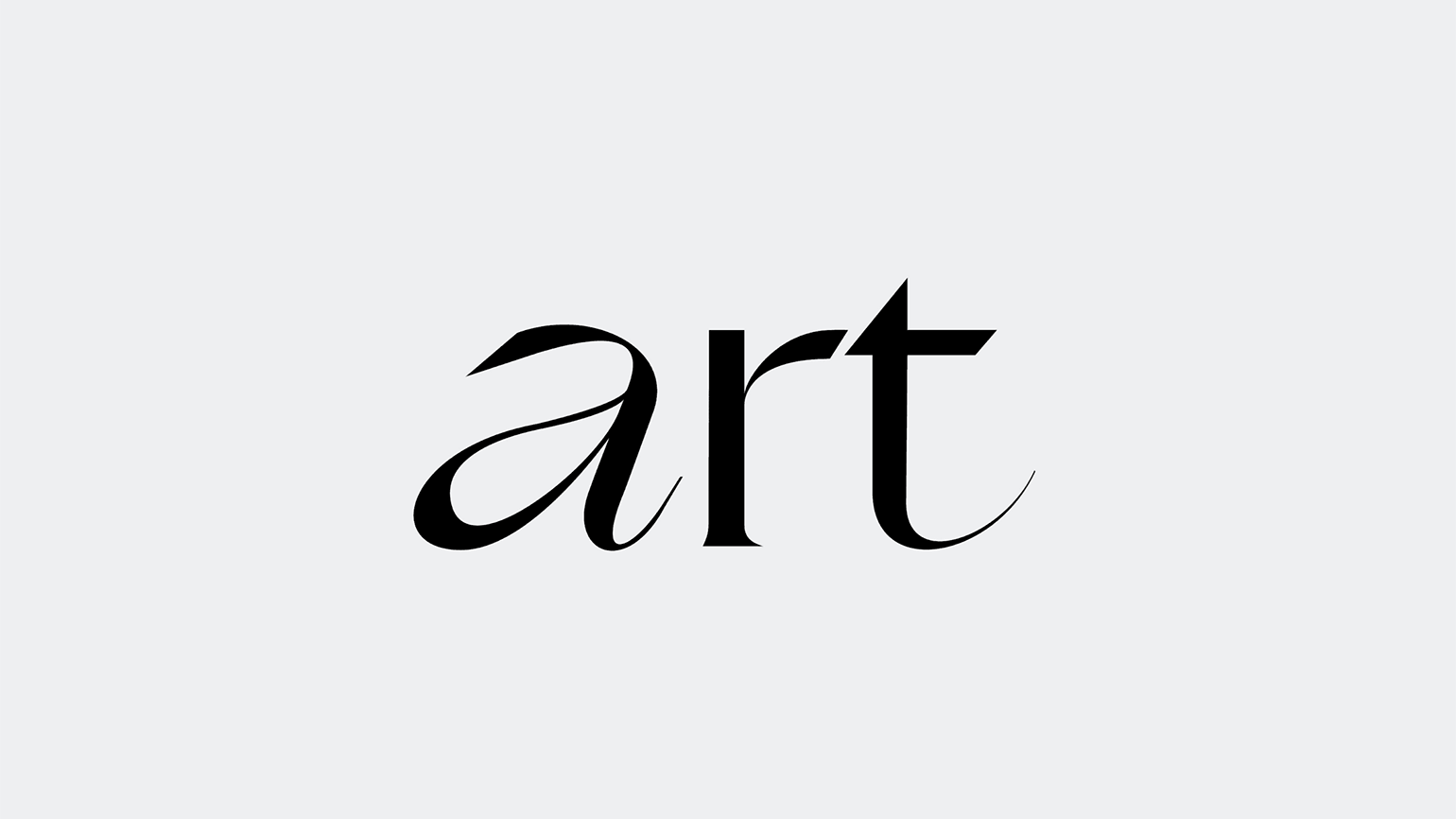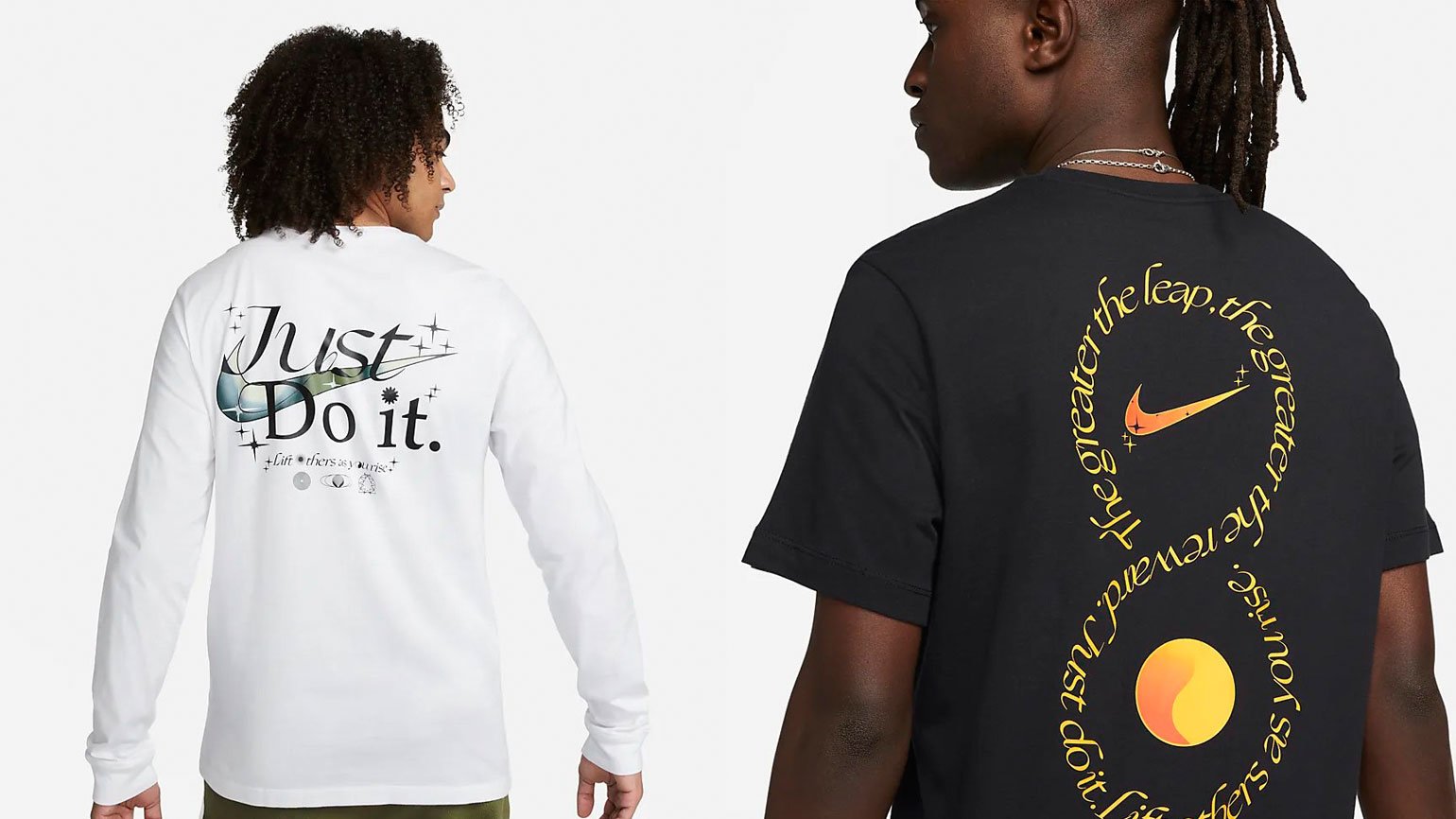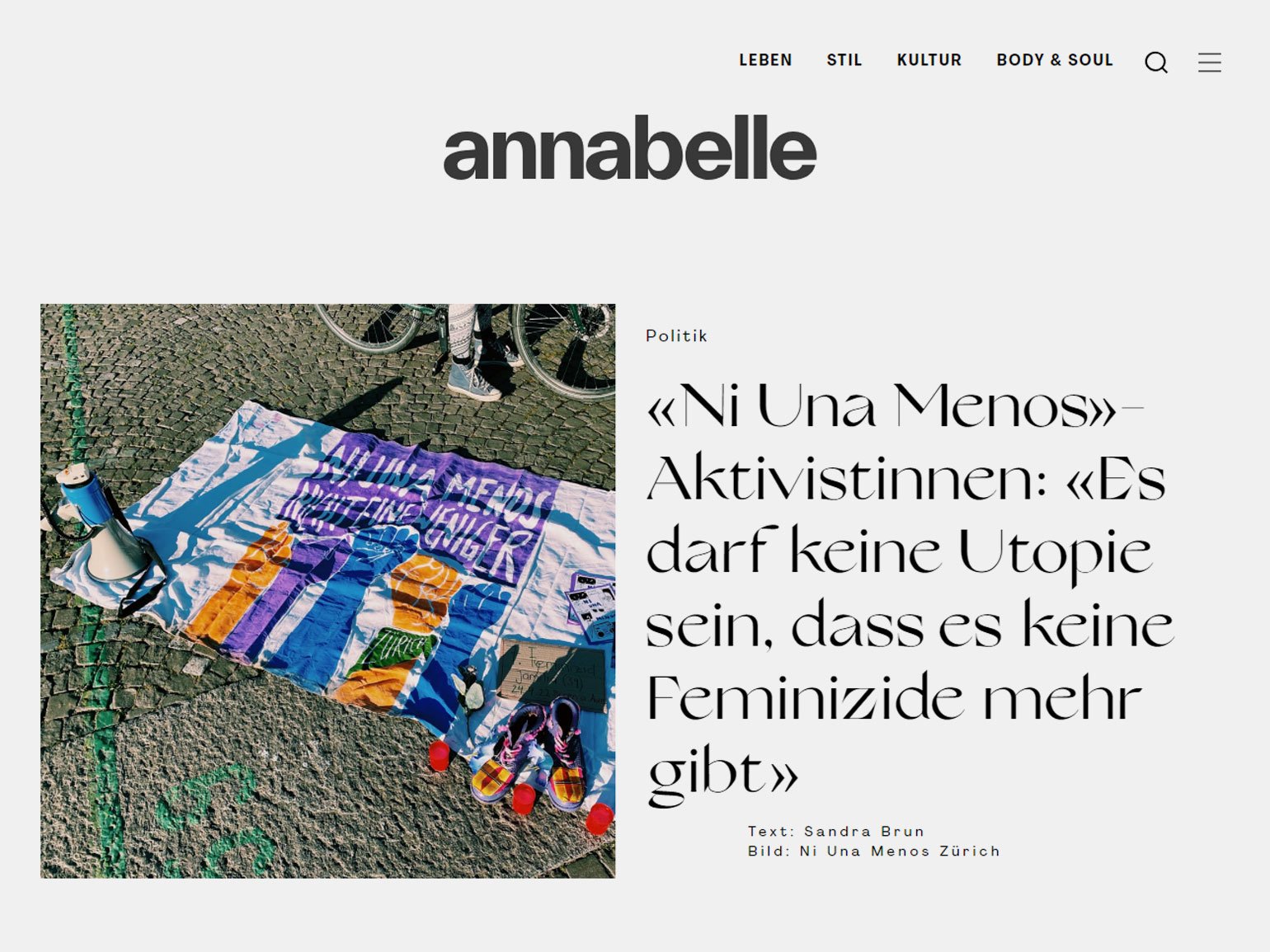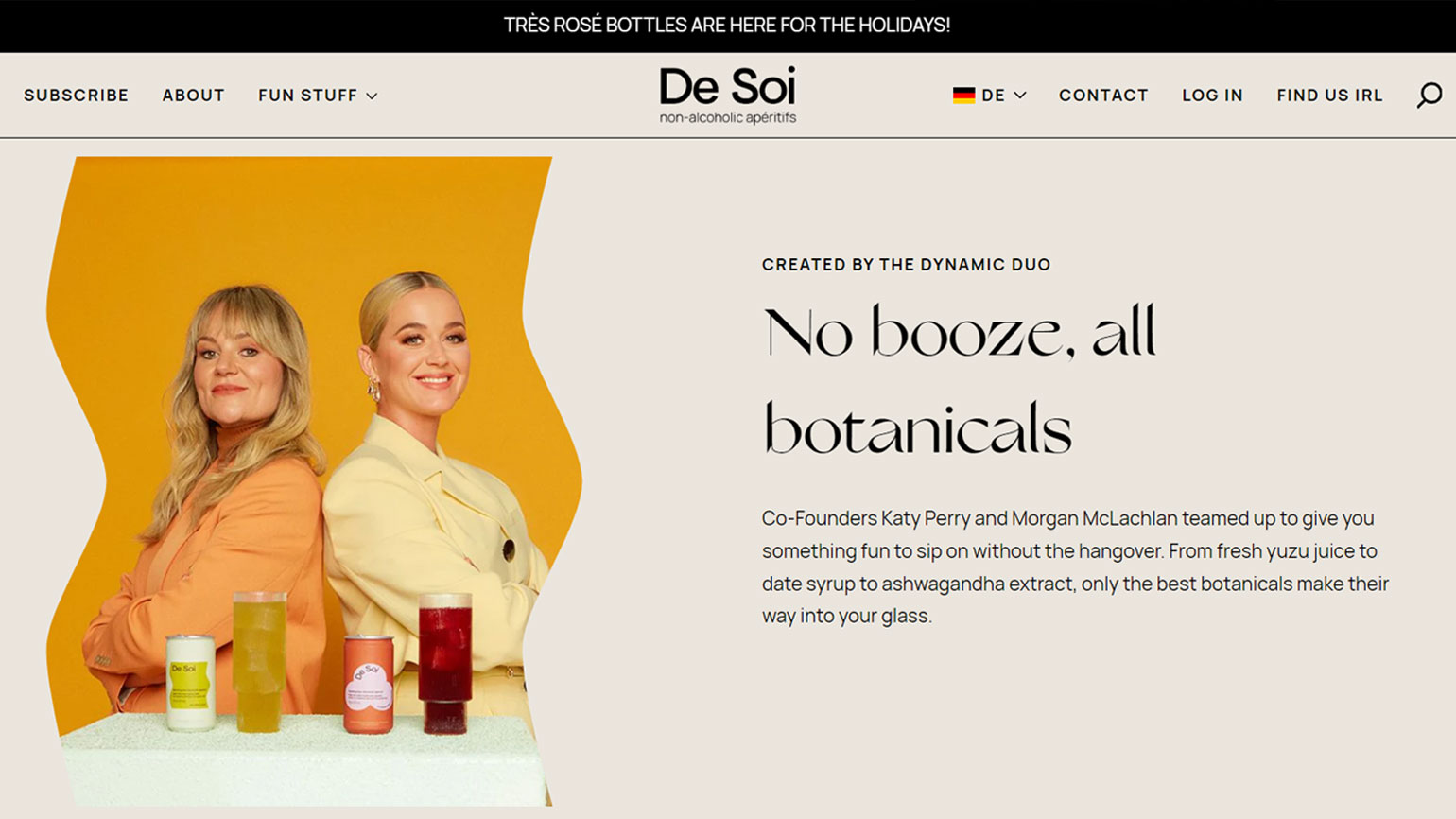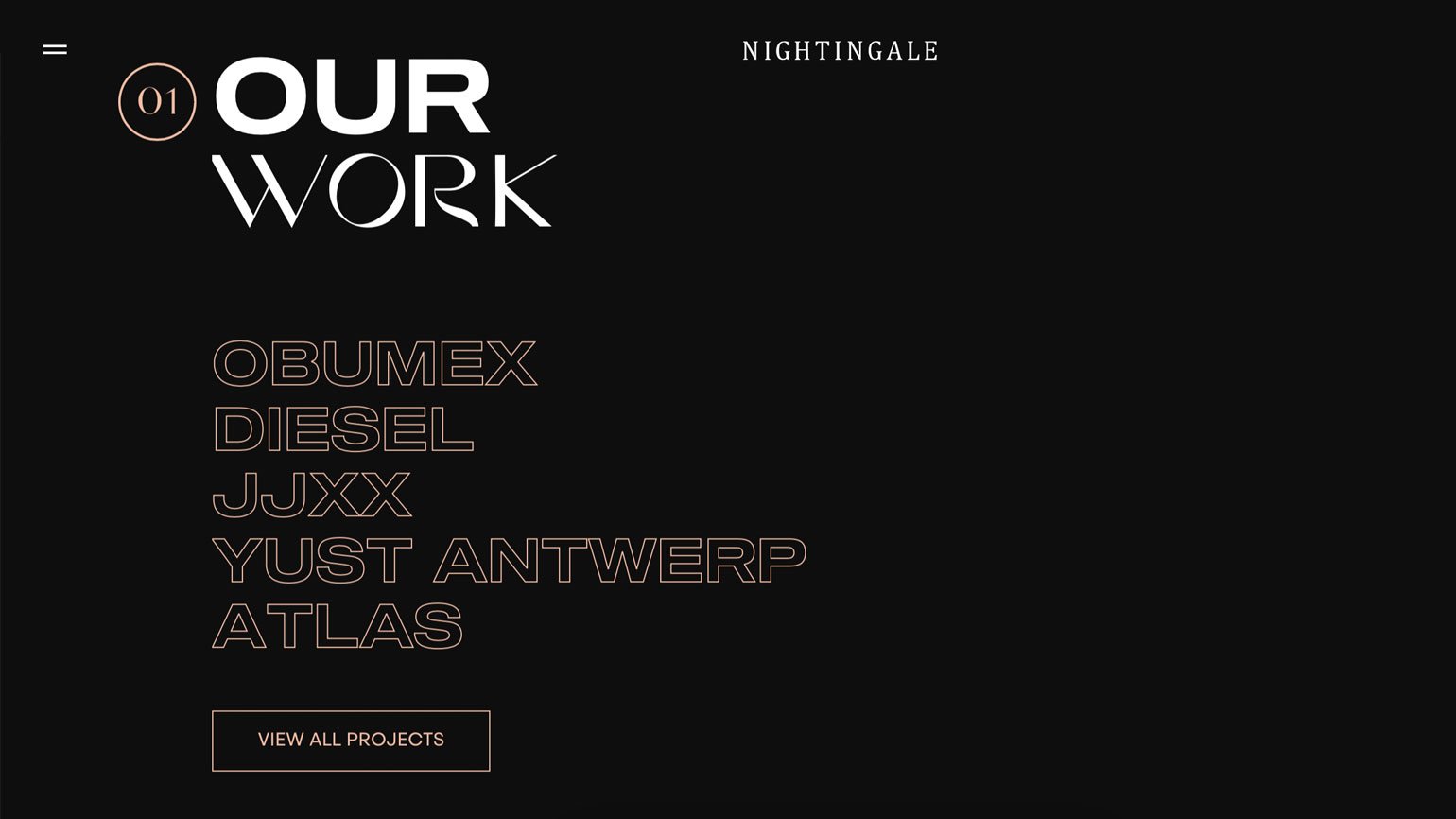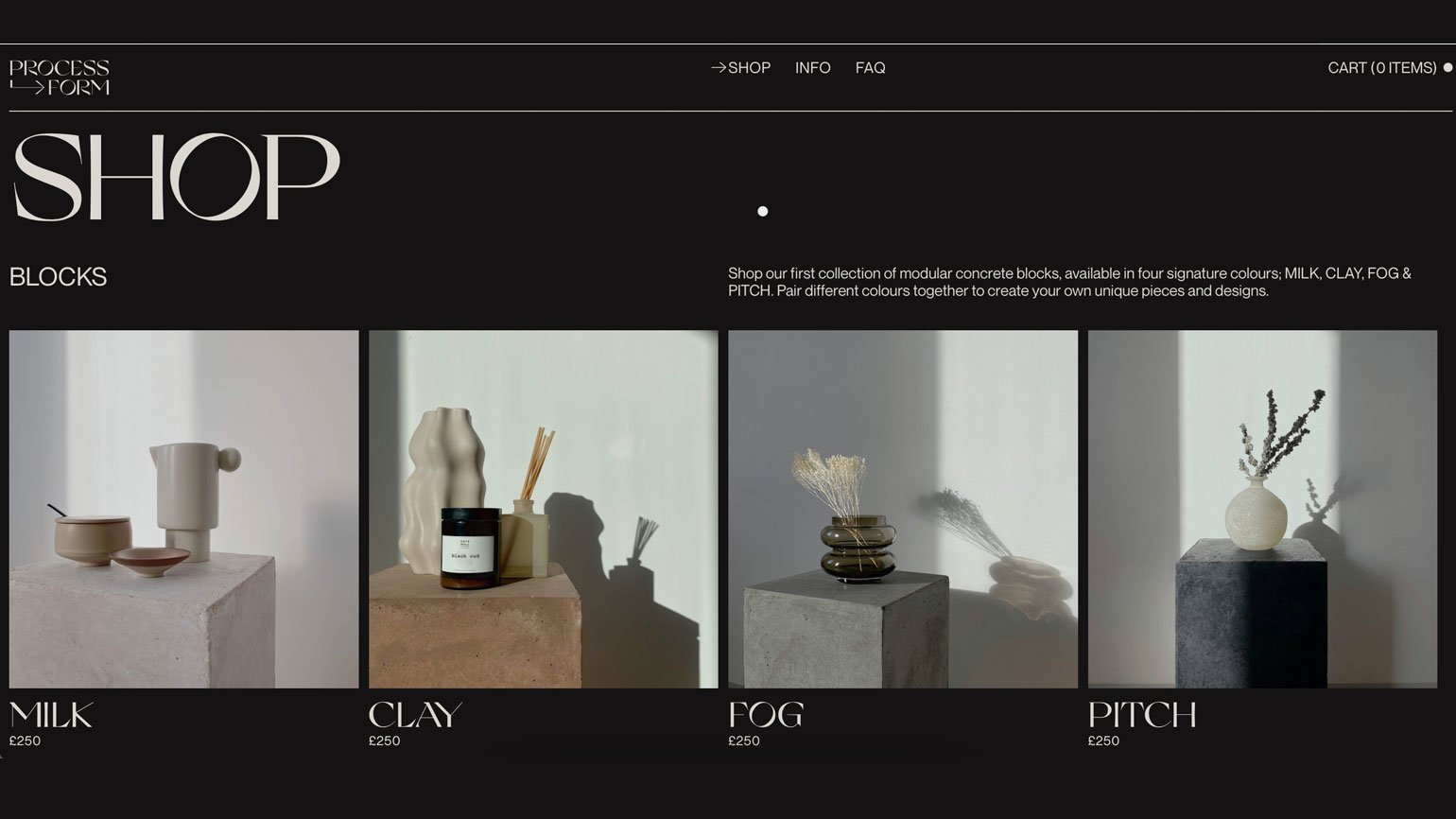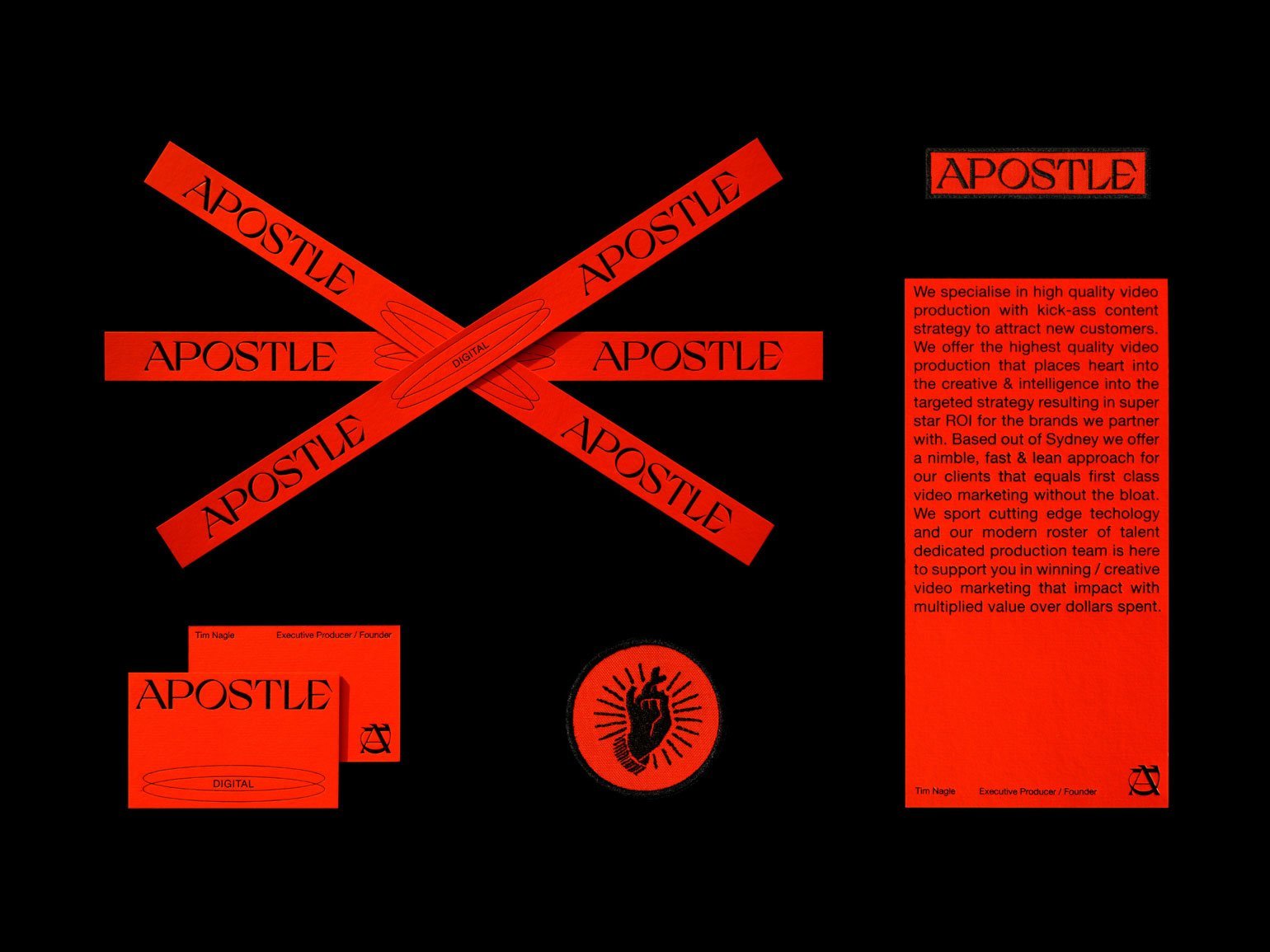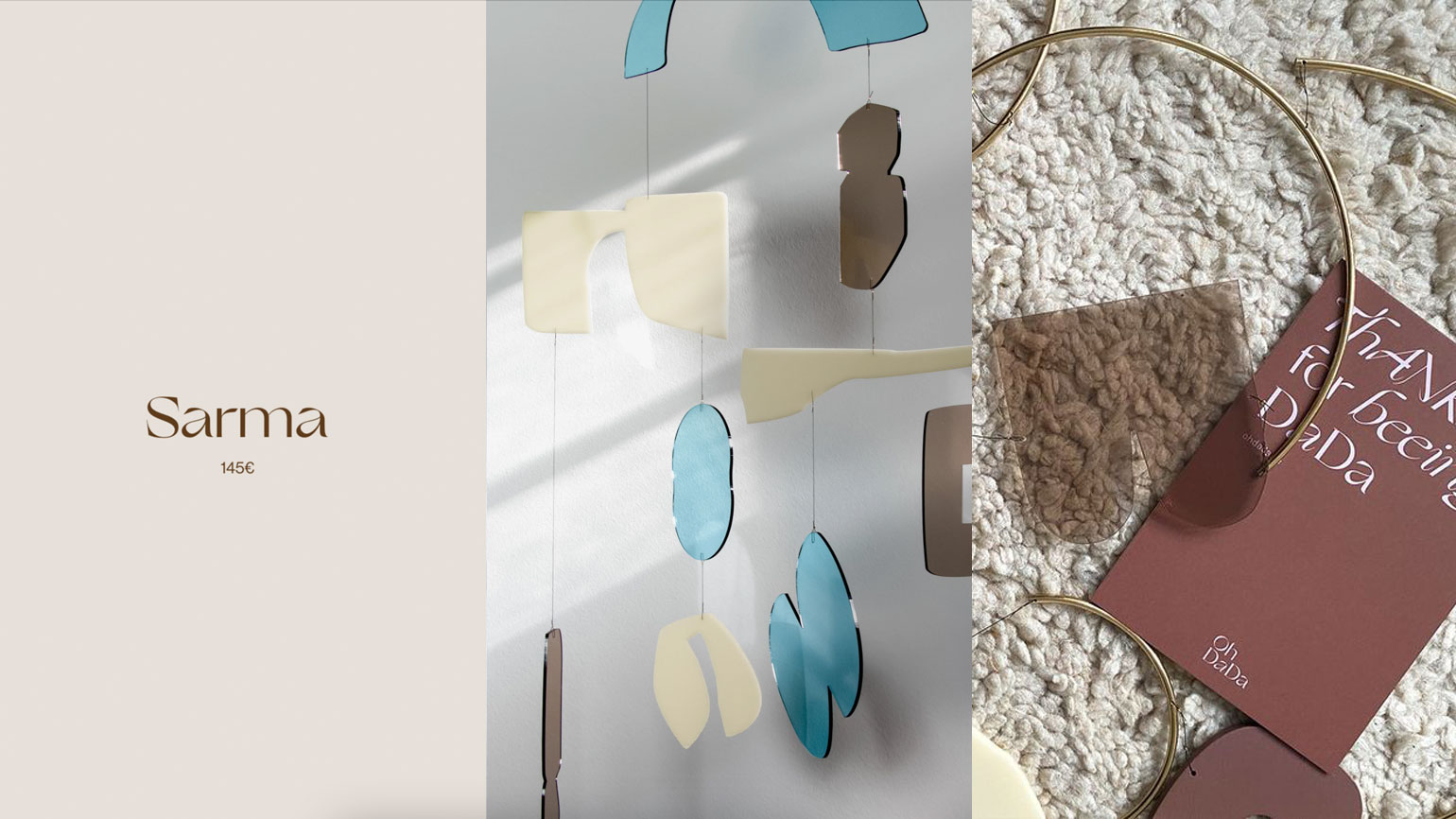
Шрифт Grand Slang: где используют и с чем сочетают
Рассказываем, для каких проектов подходит Grand Slang, и показываем примеры удачных шрифтовых пар с ним.
Разбираем модную современную гарнитуру Grand Slang: что стоит за рисунком букв, в каком дизайне её используют.
Grand Slang — что это за шрифт
Grand Slang — это набор из трёх начертаний: основного шрифта в романском стиле, курсива и версии с удлинёнными росчерками B-Side. Его выпустил в 2019 году кёльнский шрифтовой дизайнер Николас Вробель, который специализируется на изящных гарнитурах с уникальной «флюидной» графикой.
Рисунок Grand Slang особенный: в шрифте есть одновременно черты антиквы, гротеска, каллиграфического письма от руки и чёткие геометрические формы. Вробель вдохновлялся американским леттерингом середины XX века, поэтому знаки по отдельности и вместе похожи не столько на тиражный набор, сколько на произведение искусства. В буквах можно разглядеть капли, ленты, крючки, обратные засечки и нестандартные пропорции — например, B выглядит перевёрнутой, а курсивная D кажется ювелирным кулоном.
Разворот книги Оскара Огга, 1949 год. На работах этого дизайнера основывался Николас Вробель, когда создавал Grand Slang
Обложка книги Уильяма Аддисона Двиггинса — ещё одного американского мастера, вдохновившего Вробеля. Аддисон любил не только графический дизайн: ещё он увлекался созданием марионеток и кукольными представлениями
Grand Slang в презентации автора
В кассе Grand Slang расширенная латиница, есть лигатуры, символы основных валют и распространённые знаки препинания. Кириллицы и греческого алфавита нет.
По визуальному характеру Grand Slang свободный, эмоциональный, эксцентричный и, несмотря на то что создан с оглядкой на леттеринг 1940–1950-х, явно современный и диджитальный. Все тонкие линии — идеально тонкие, срезы — идеально срезанные, а асимметрии — непредсказуемые.
Практически сразу после релиза Grand Slang стал очень популярным инструментом дизайна, особенно для айдентики fashion- и beauty-брендов.
Grand Slang в дизайне коллекции для Nike
Выразительный Grand Slang отлично сочетается с нейтральными гротесками. Например, такую шрифтовую пару используют в дизайне онлайн-журнала для женщин Annabelle. Это швейцарское медиа, в котором публикуют материалы о моде, красоте, политике, проблемах статуса и свобод.
Шрифтовая пара Agrandir и Grand Slang
Посмотрим, как Grand Slang используют в дизайне лендингов и книг, упаковке и брендинге.
Grand Slang в вебе
De Soi — компания певицы Кэти Перри и предпринимательницы Морган МакЛахлан. Под этой маркой производят здоровую альтернативу алкоголю — лимонады-аперитивы со вкусом классных коктейлей, но без спирта.
Броские заголовки на сайте оформлены Grand Slang, а основной текст — Manrope: первый привлекает и визуально выражает идею веселья, а второй успокаивает дизайн и делает ToV дружелюбнее.
Шрифтовая пара Grand Slang и Manrope
Для собственного сайта студия Nightingale собрала сложную схему типографики. В дизайне соединили неогротеск Sequel в насыщенности Black, фантазийный Grand Slang и закрытый Steradian. Такие эксперименты со шрифтовыми парами неоднозначны, но помогают создать образ креативной и смелой команды.
Шрифтовая пара Steradian, Grand Slang, Sequel
Process Form — британская креативная пара, которая создаёт предметы декора и объекты из бетона. В дизайне онлайн-магазина этой марки фокус на минималистичности простой сетки и монохроме, и единственный «нарядный», привлекающий внимание элемент — это заголовки, набранные Grand Slang.
Шрифтовая пара Neuemontreal и Grand Slang
Grand Slang в айдентике
Студия Mubien работала над проектом для видеопродакшена Apostle Digital в 2020 году. Эта австралийская компания создавала ролики и маркетинговый контент для Adidas, Gucci и локальных австралийских брендов.
Айдентику построили на высоких контрастах: сочетании глубокого чёрного и сияющего красного, нейтрального Neue Helvetica и блистательного Grand Slang.
Шрифтовая пара Grand Slang и Neue Helvetica
Ещё один пример сочетания «гельветики» и шрифта с обилием декоративных деталей — фирменный стиль марки интерьерных мобилей. Логотип и заголовки оформлены Grand Slang, а дескрипторы — Neue Haas Grotesk.
Шрифтовая пара Grand Slang и Neue Haas Grotesk